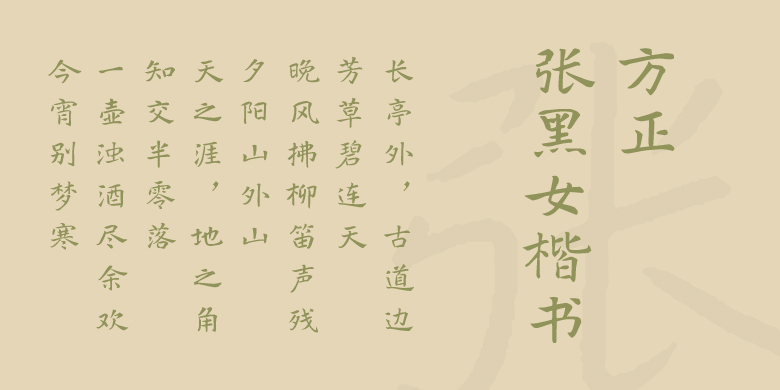
方正张黑女楷书
• 整理/设计:
郭毓海
楷书、常规书写·毛笔
关于张玄墓志:
《张玄墓志》,全名《魏故南阳张府君墓志》,又名《张黑女墓志》,刻于北魏普泰元年(531年)。其书法集劲健、秀逸、含蓄于一体,堪称北魏墓志书法的巅峰之作。清代书家何绍基盛赞其“遒厚精古,未有可比肩者”。
字体特征:
用笔方圆兼备,横画圆起方收,长捺一波三折,结体扁方兼有隶意。字体古雅、秀逸、含蓄而多趣。兼顾排版要求和当代字形规范,实用性佳。
设计师:郭毓海